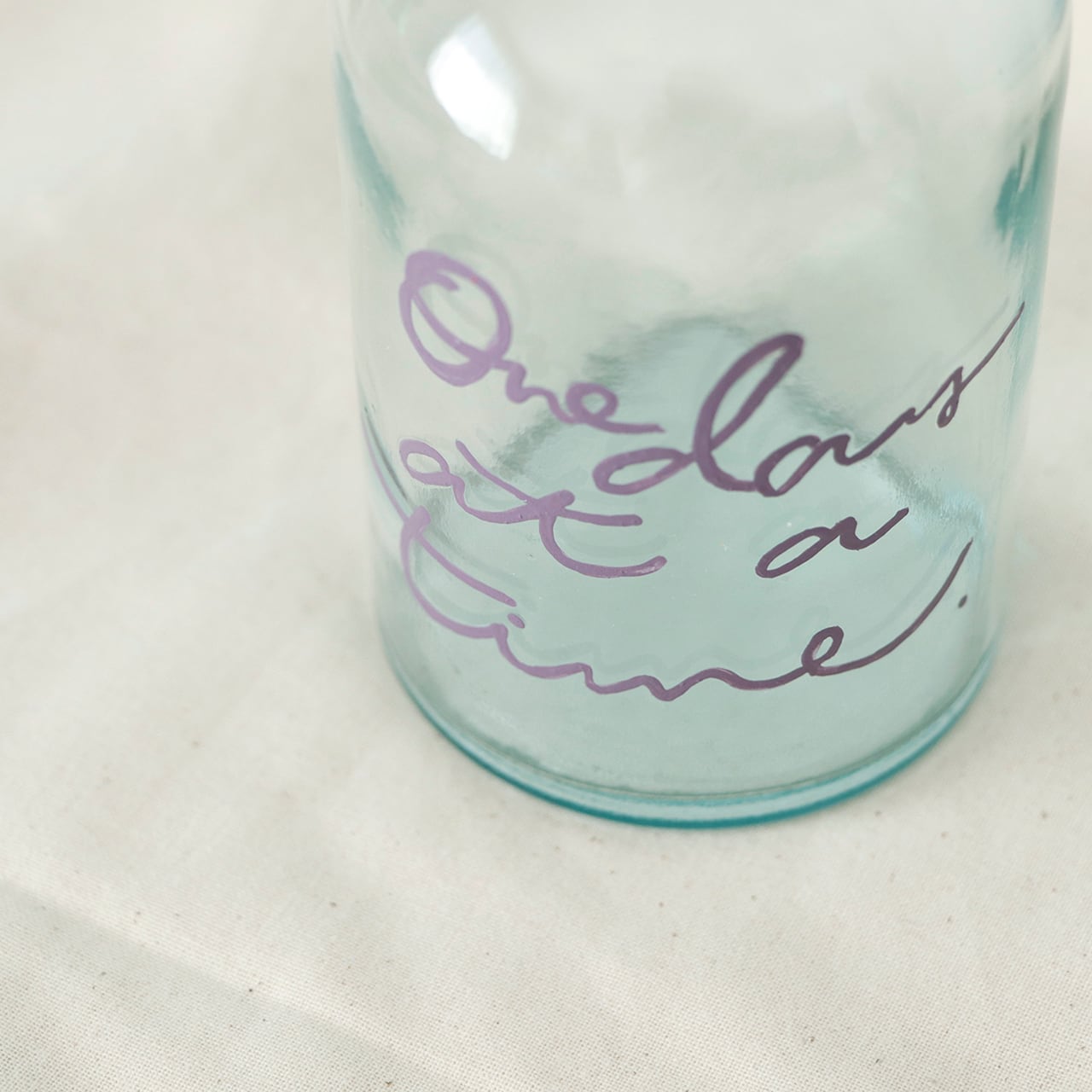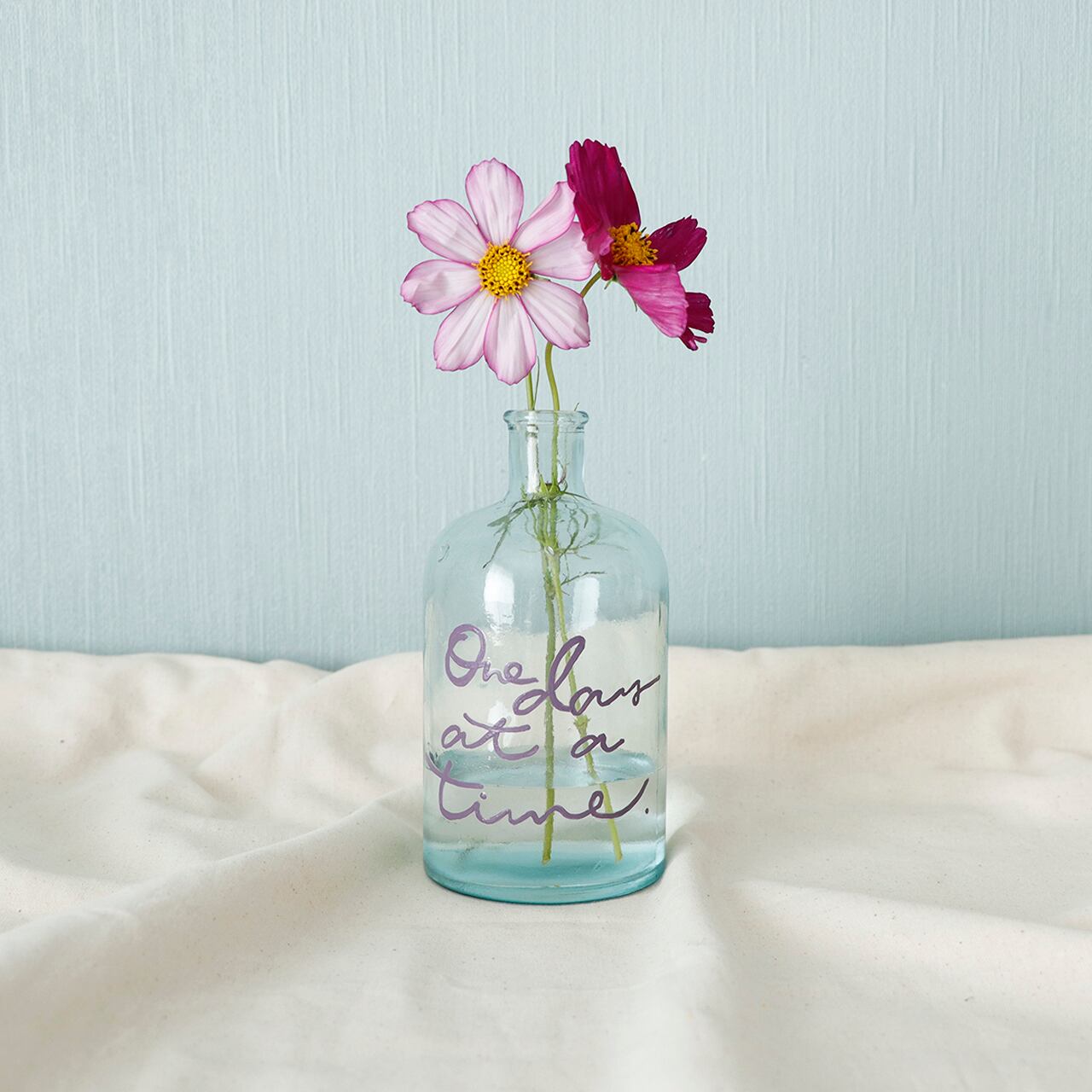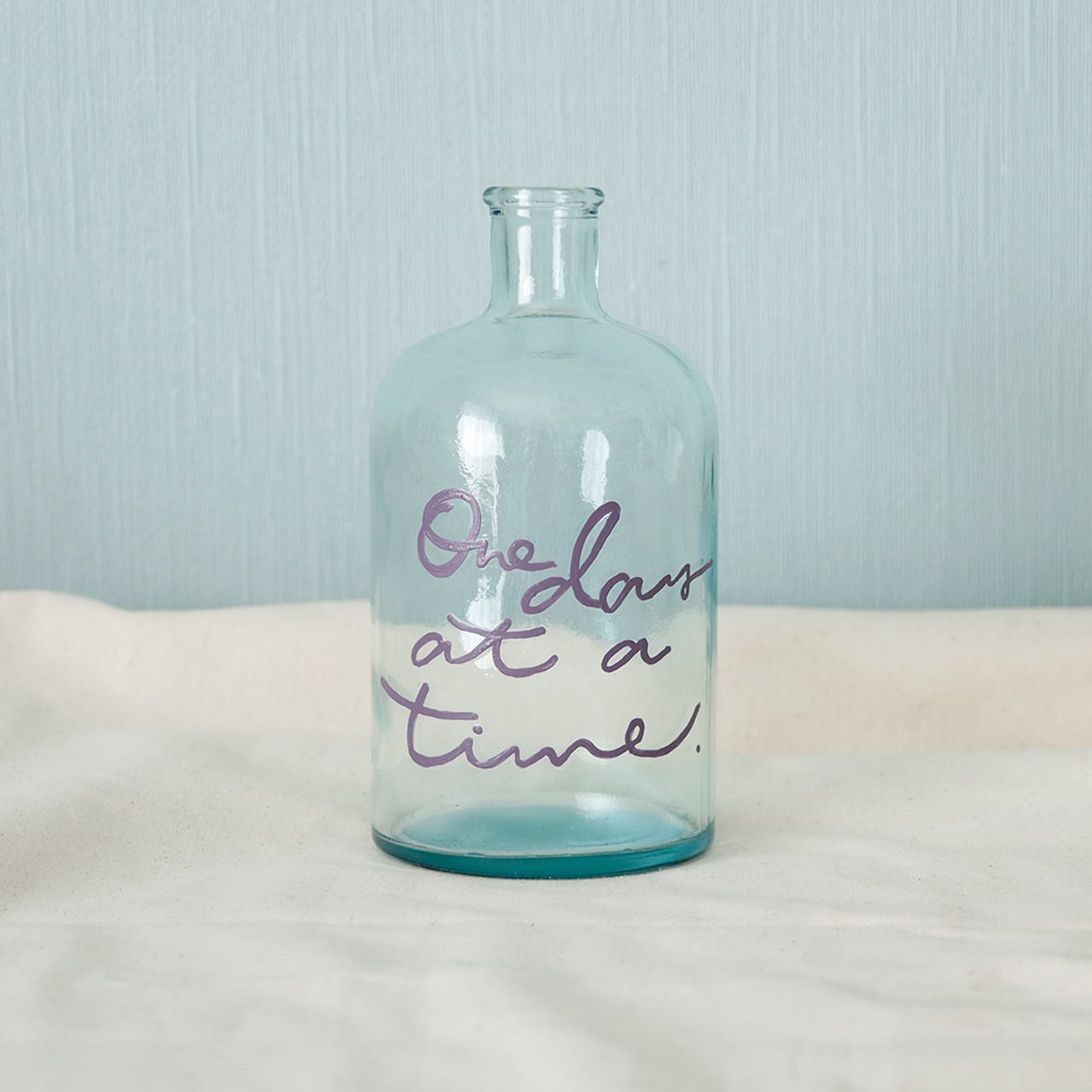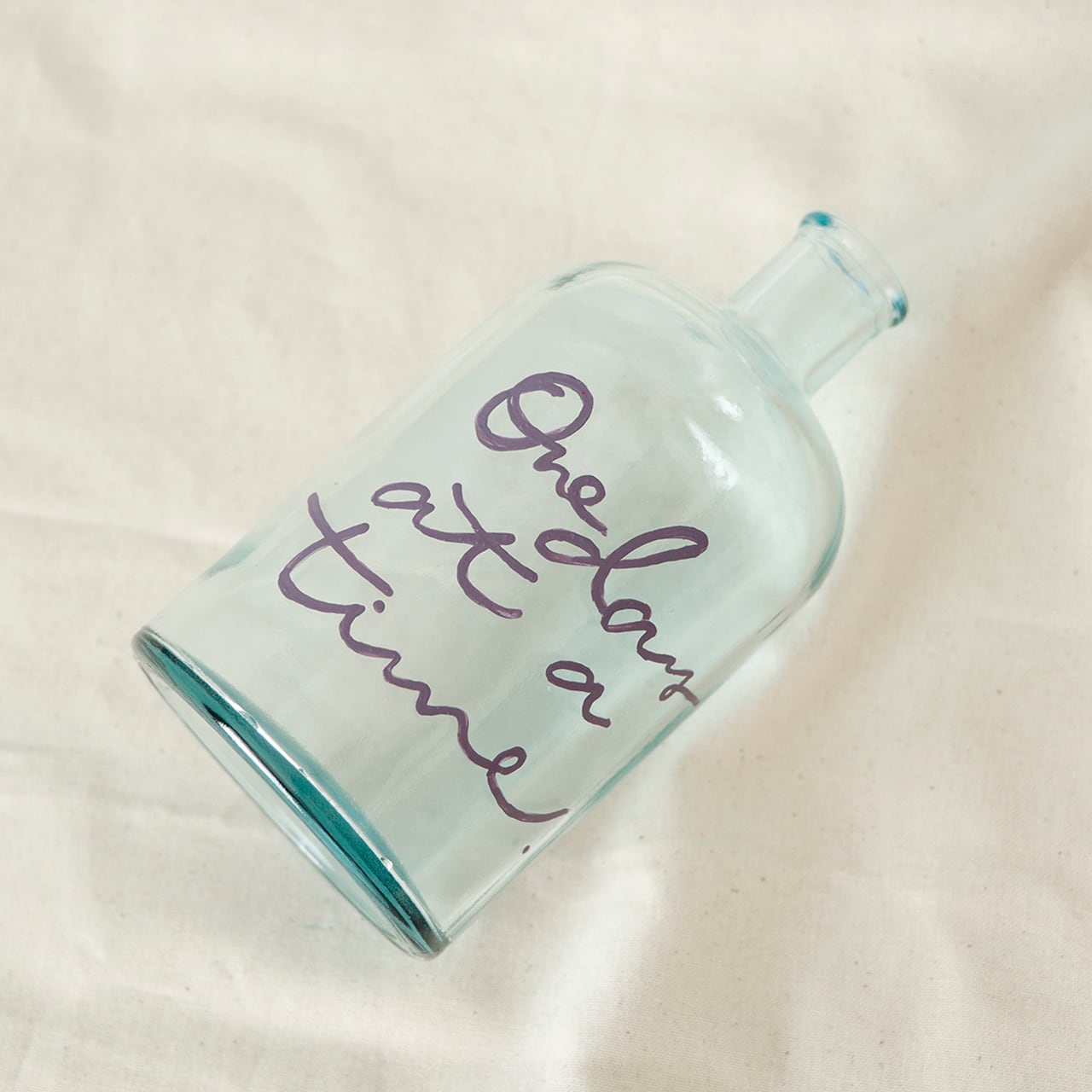
【BOTTLE PAINT ART】One day at a time.
One day at a time
1日1日
1日少しずつ。
コツコツと、でも着実に進みたい時に声に出したい言葉。
花瓶として、そのまま飾ってディスプレイとしても◎(食用はおすすめしません)
光が入るとこに置くと、瓶の色とともに文字も影になって素敵ですよ!!
空き瓶に文字を直接ペイントしています。クリアコーティングしていますが、引っ掻きに弱いので取扱いの際はご注意ください。